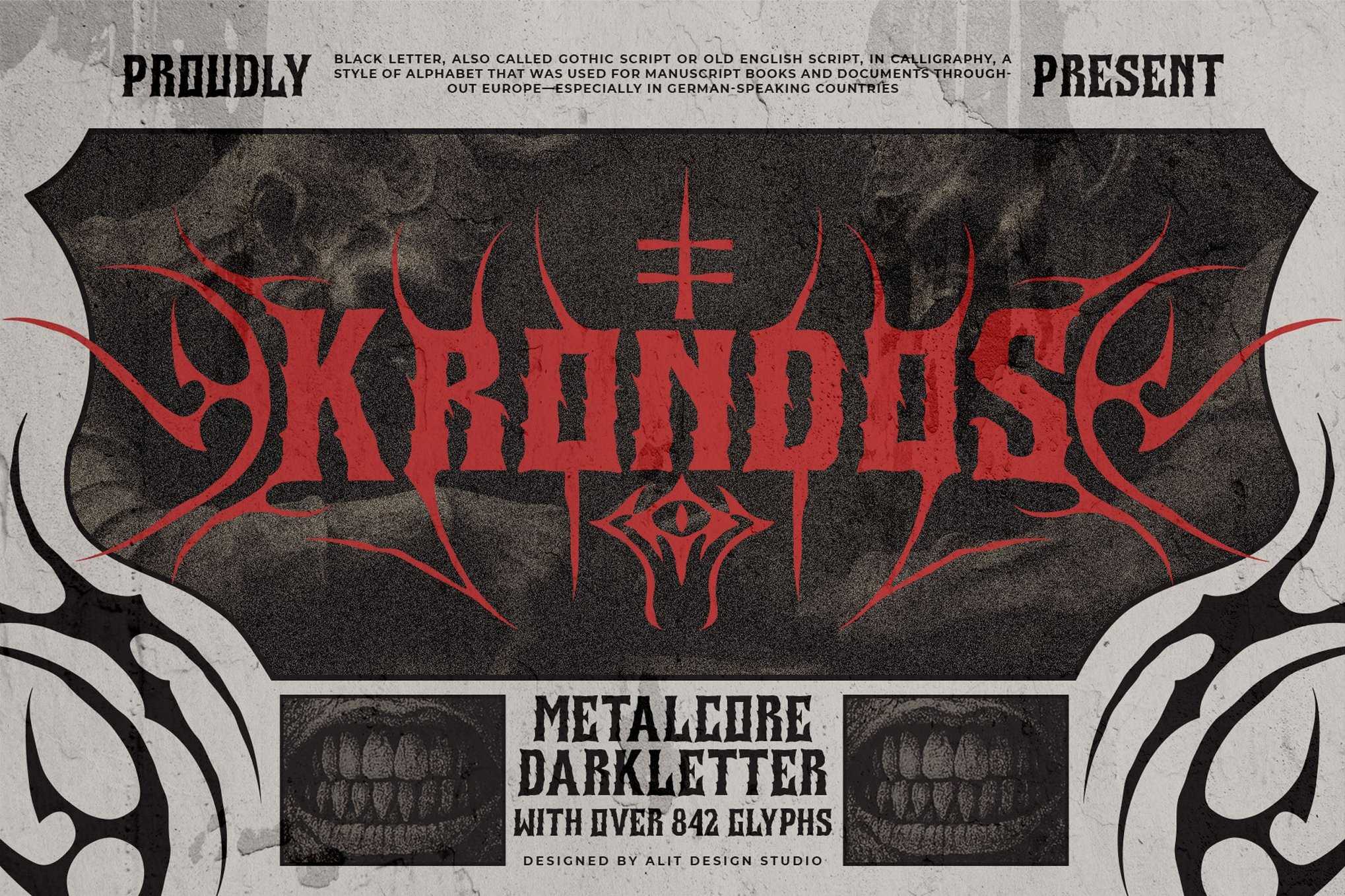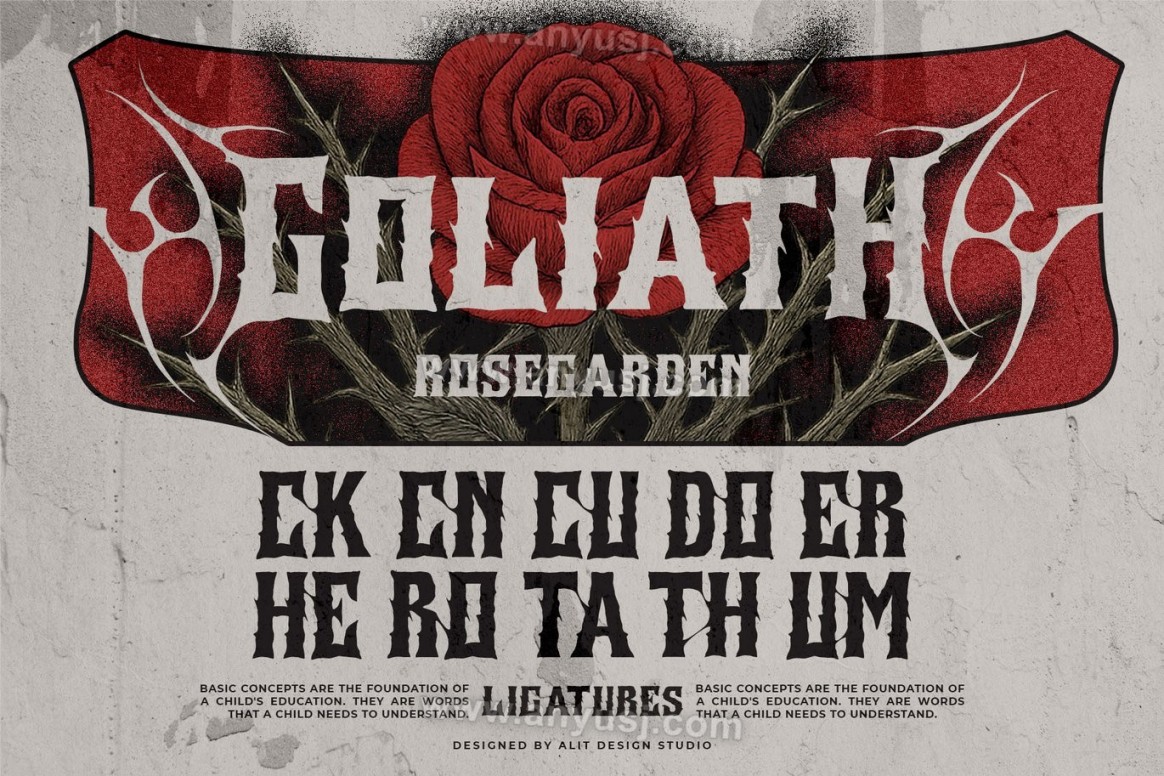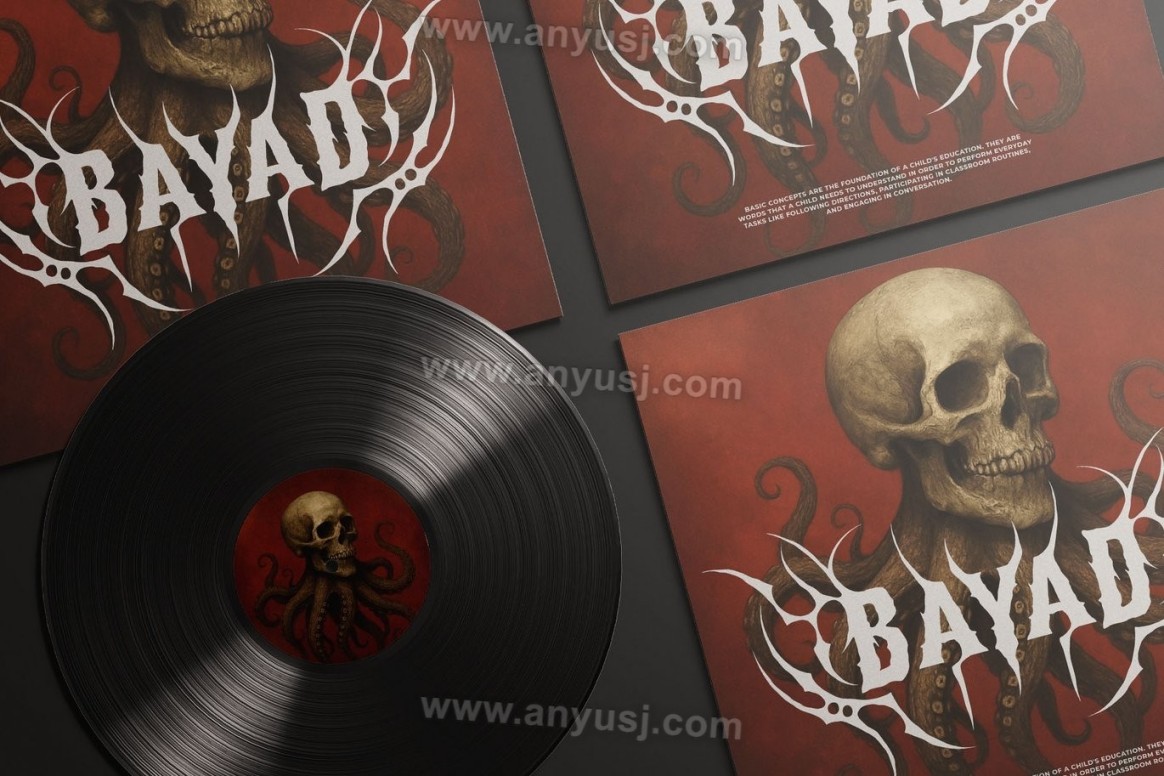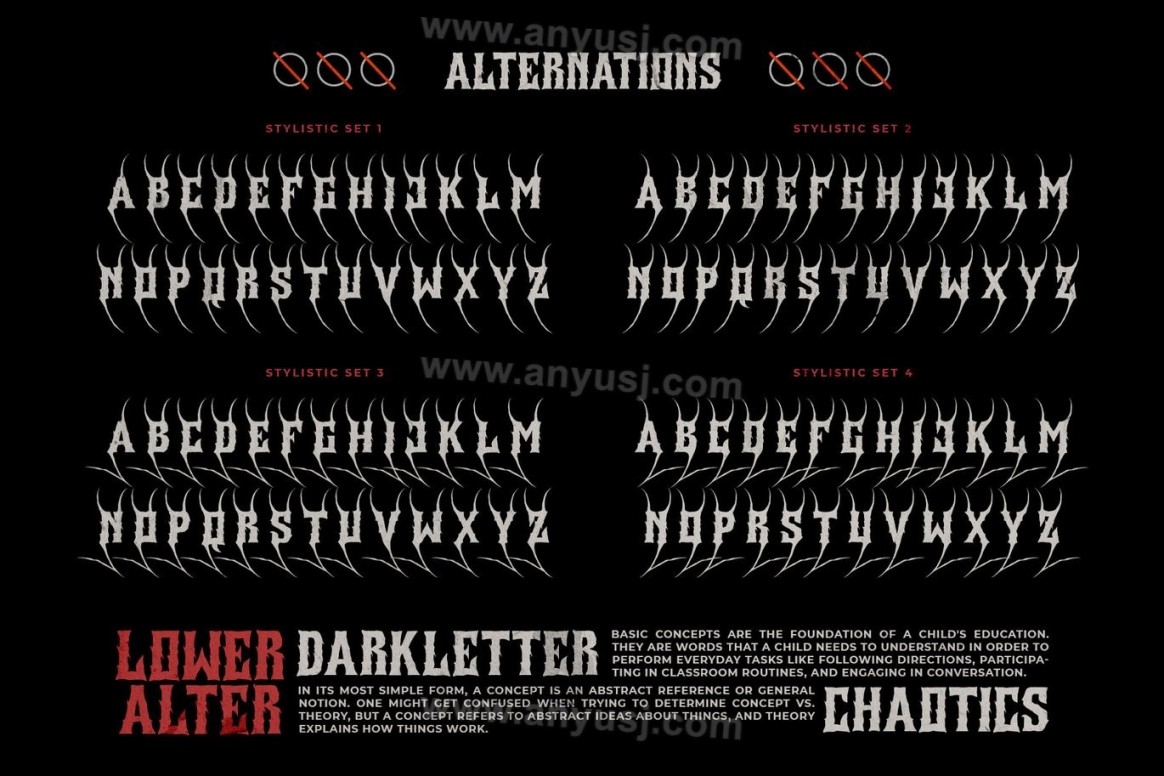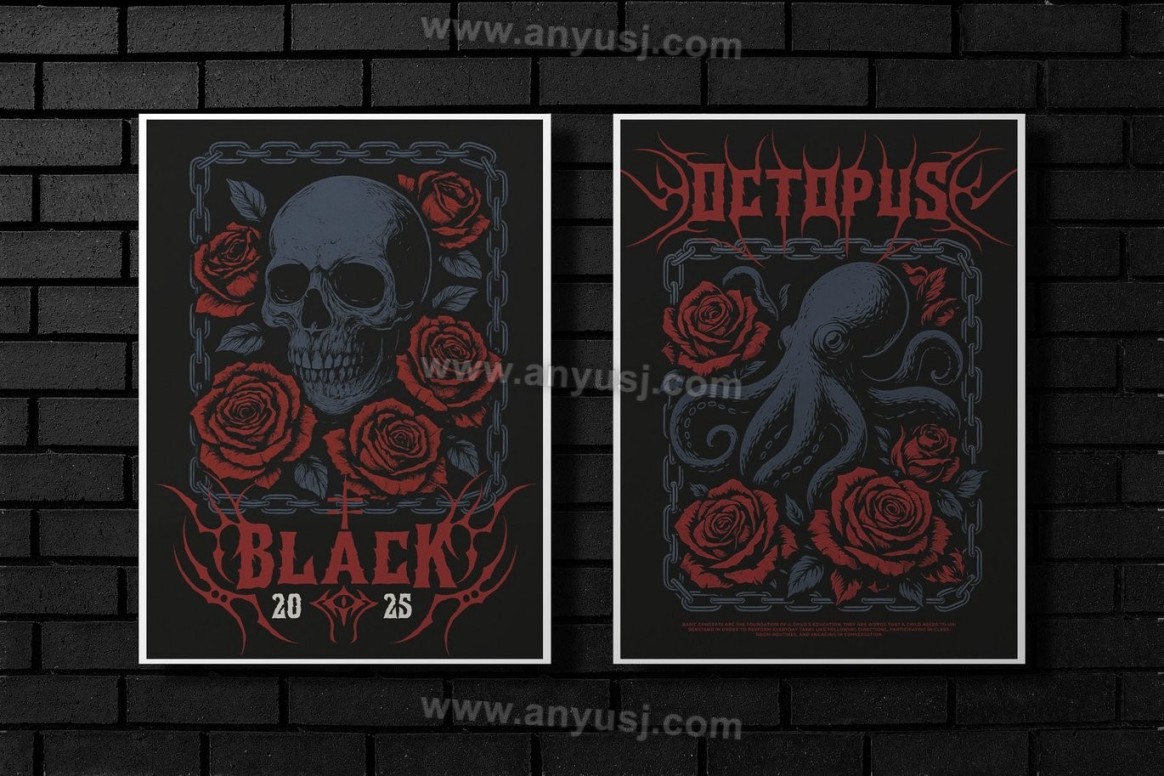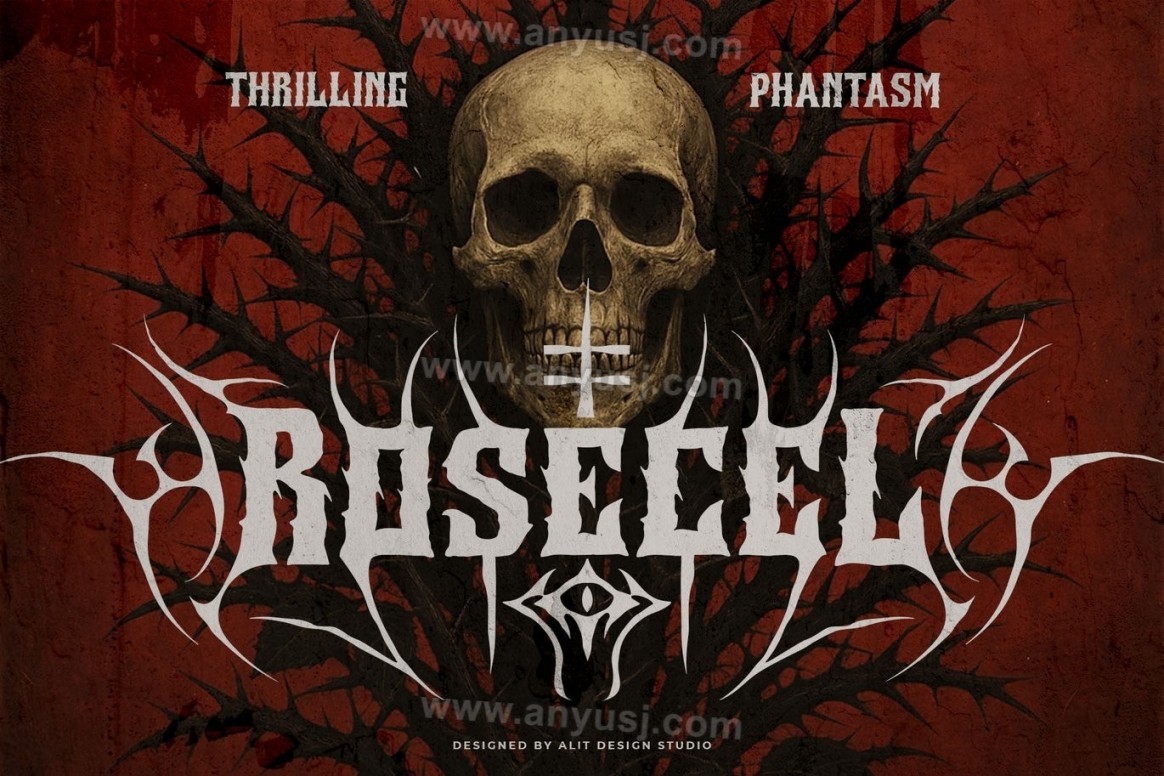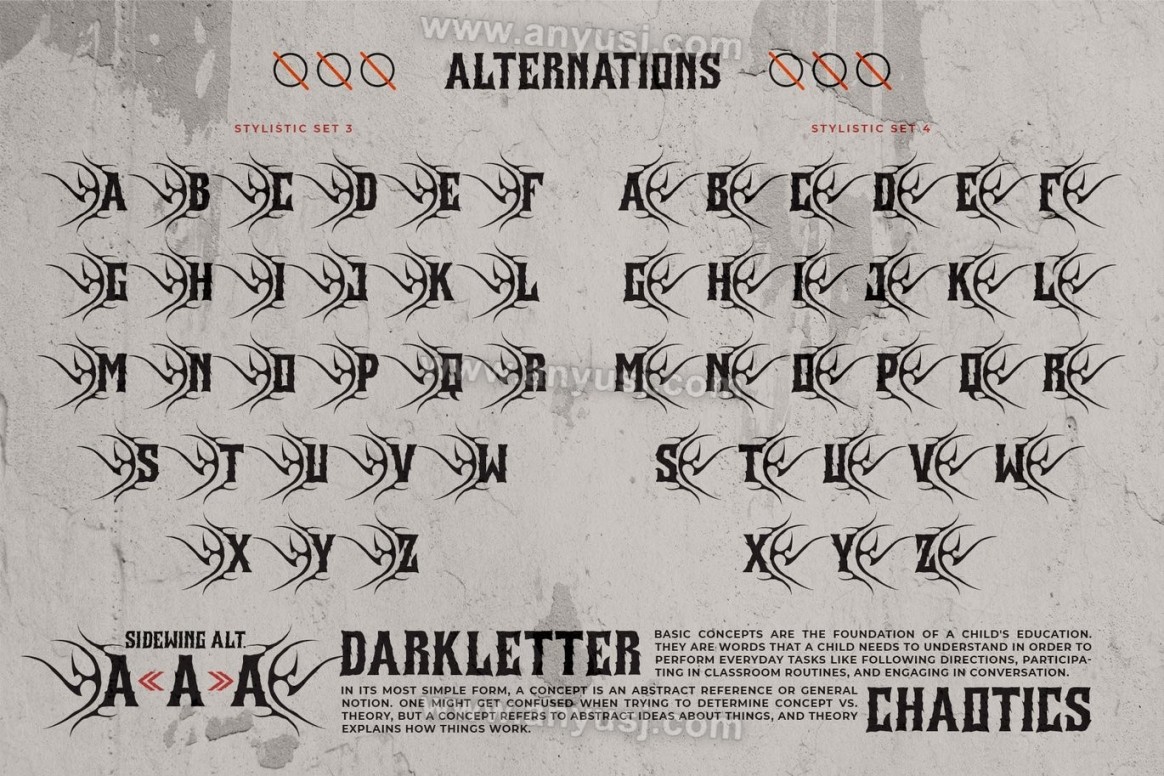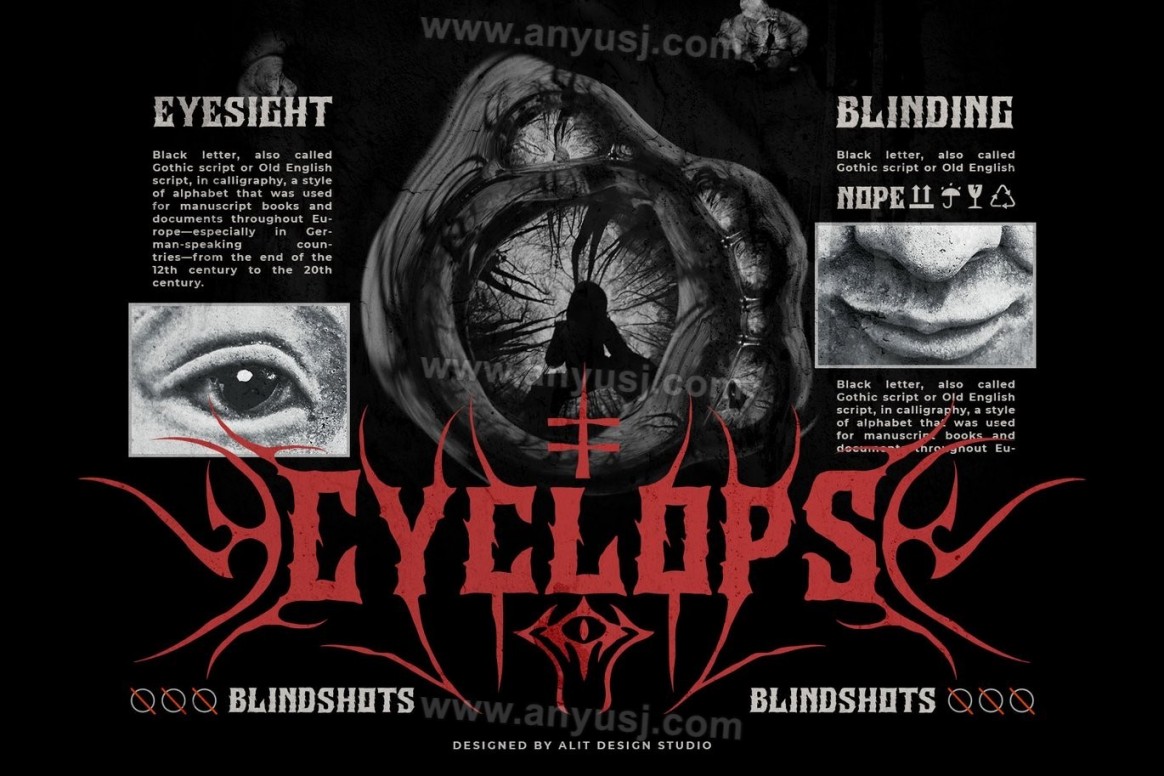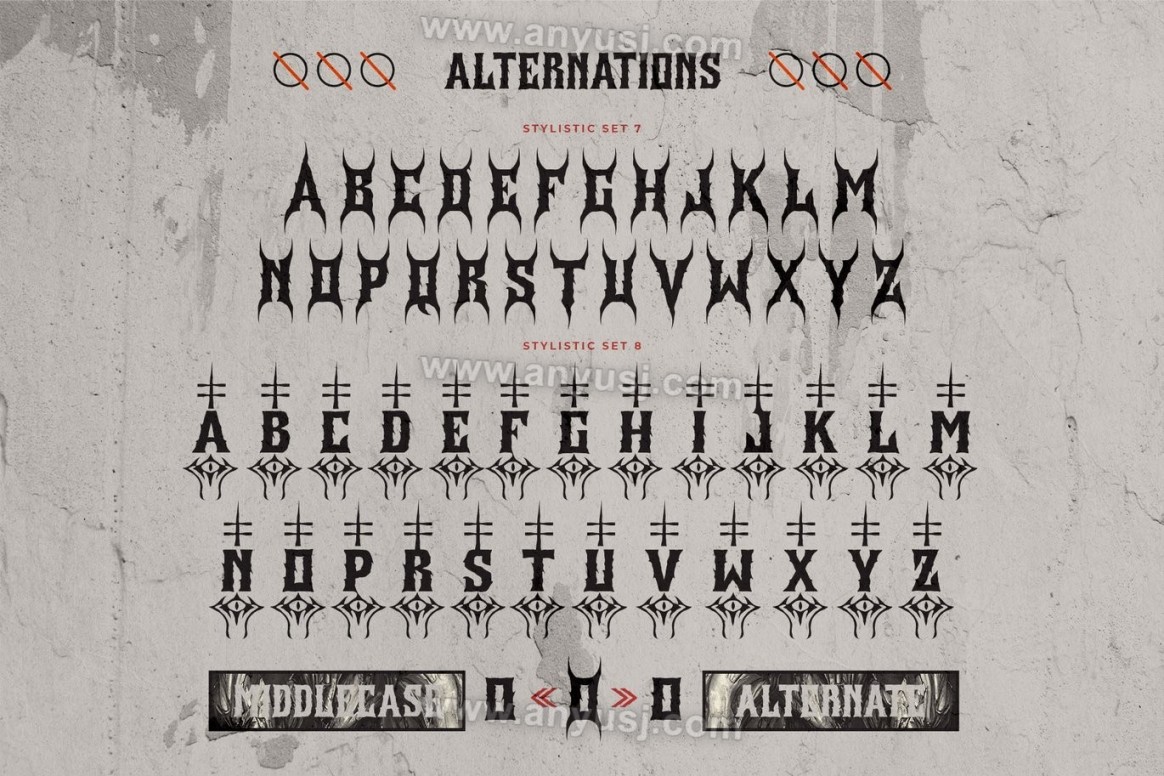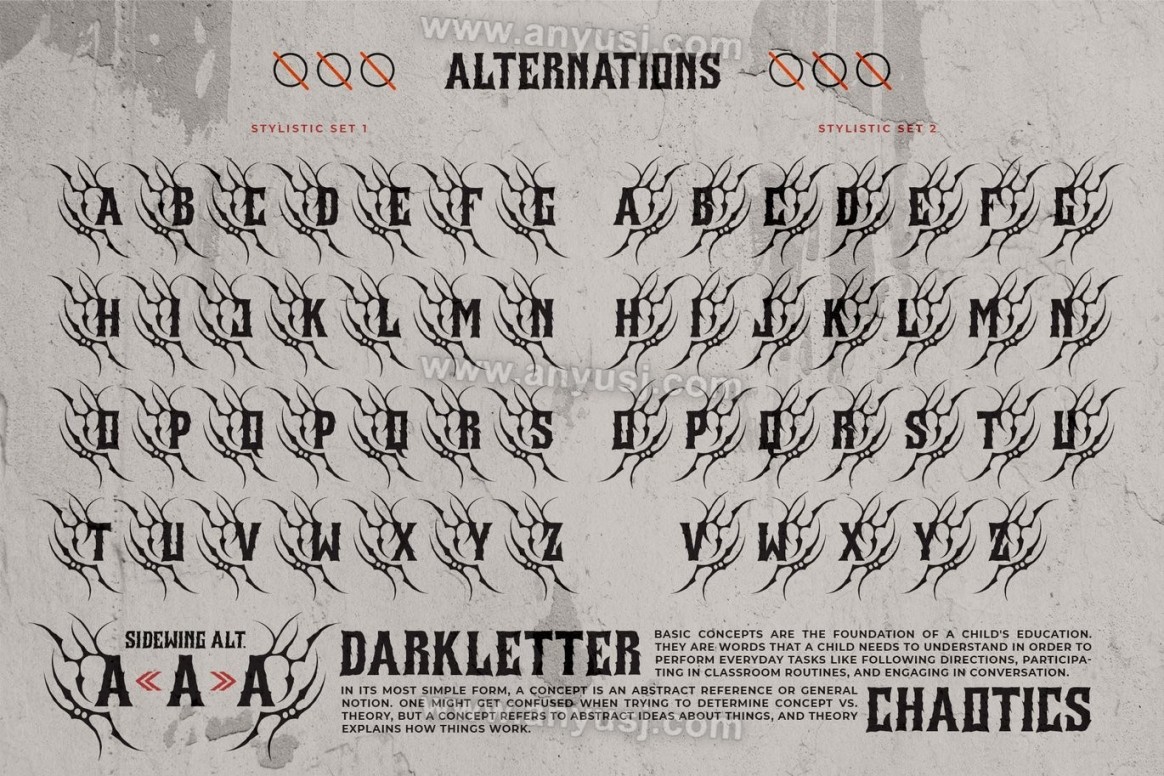
复古哥特式金属摇滚荆棘恐怖锋利logo徽标标题排版西文英文装饰字体Krondos Font
Krondos字体——来自阴影的字体
Krondos字体是从被遗忘的文字库中召唤出来的,不适合胆小的人。
Krondos是一种哥特式金属风格的字体,充满了荆棘的卷须,形状像黑社会根源,将恐怖与和谐融为一体。每一封信都是精心制作的,就像一座被诅咒的森林的古代雕塑——扭曲、锋利、生动。然而,在其令人难忘的表面之下,有一种惊人的清晰度,使其非常适合从闹鬼事件海报到黑暗幻想游戏的所有内容
以及地下音乐品牌。
Krondos拥有超过842个隐藏在其深处的字形,包括神秘的替代品和怪异的符号,为您提供了召唤真正邪恶事物的工具。
☠️ 坟墓里有什么:
可怕的、根状的角色,有着邪恶的转折
超过842个字形(是的,真的!)用于无尽的黑暗创造力
非常适合金属乐队、恐怖杂志、噱头标志和诅咒产品
可读性足以耳语你的信息。。。带有威胁
敢于用死者能读懂的声音写作。
克朗多斯字体——雕刻你的信息
在阴影中。